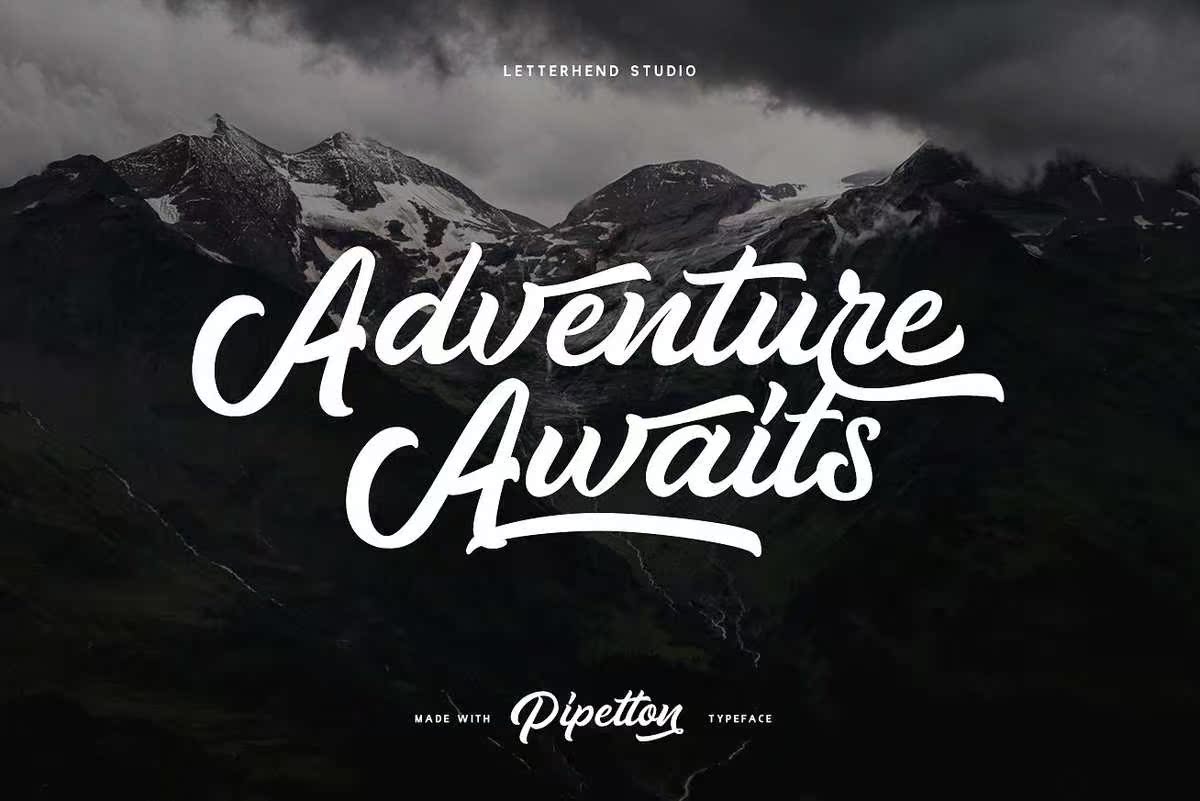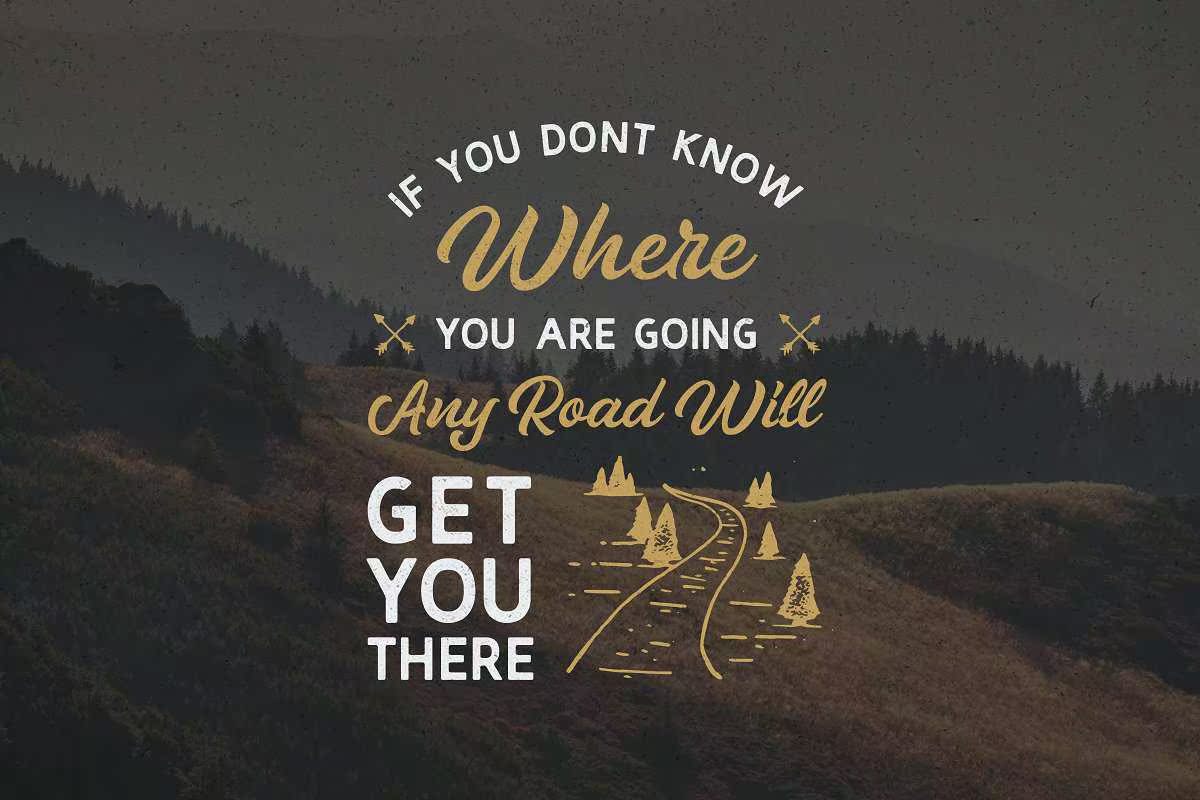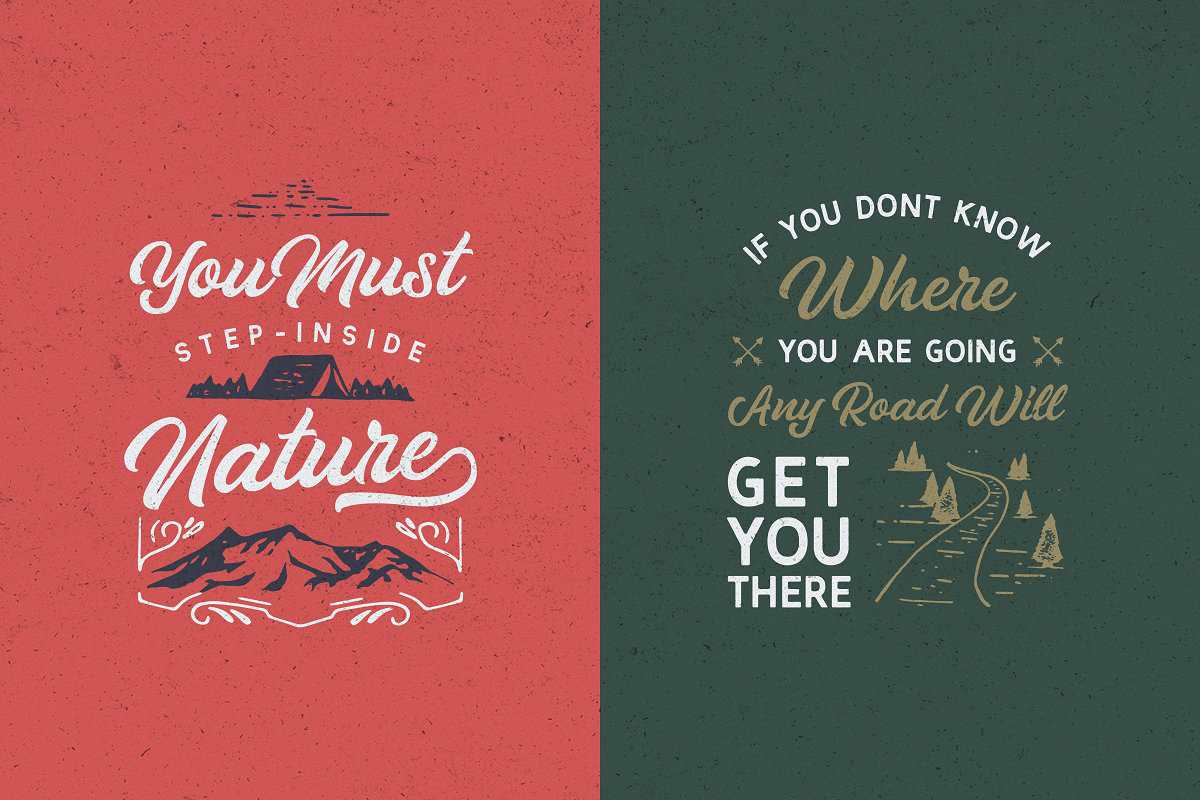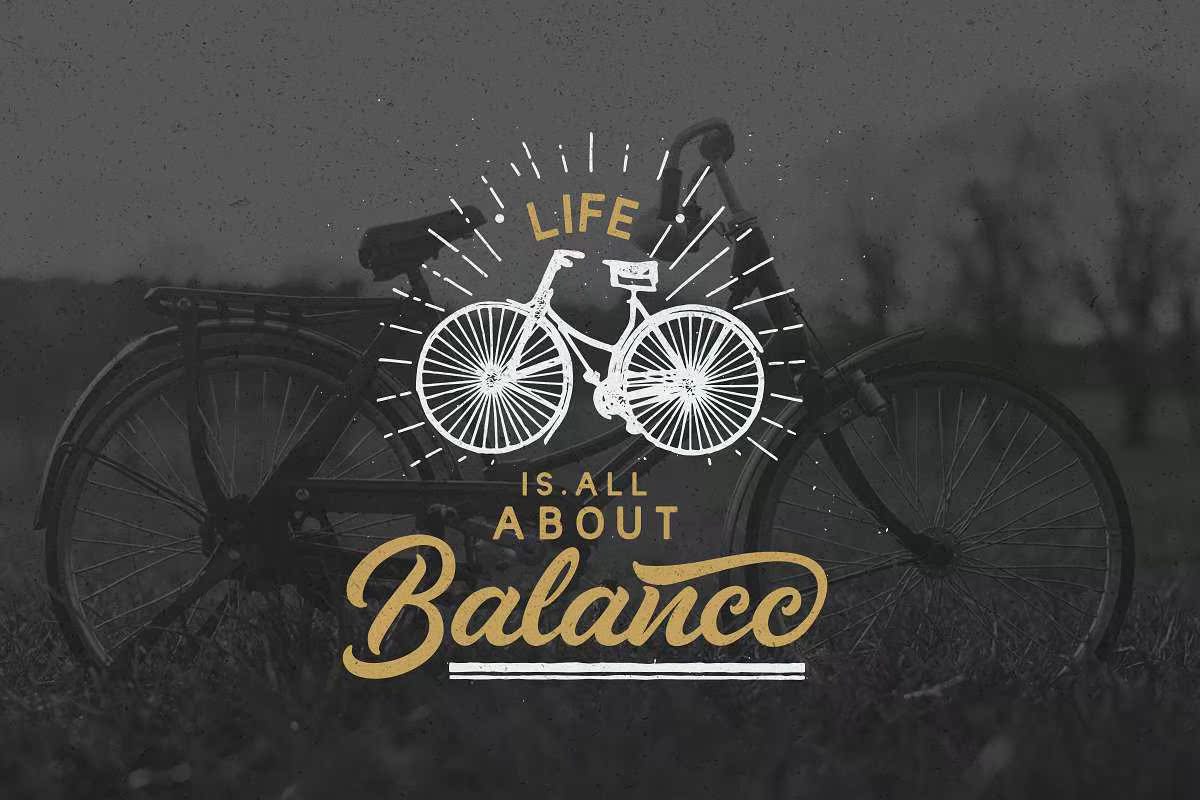
此字体由两种字体组成,分别是主脚本字体和互补字体,以及完全匹配的字体。此字体可使用易于识别的字体/文字标记/标签等,其字体和粗体字符使其不受排挤。此字体包括大写、小写、标点符号、符号和数字、样式集替换、连字和Swash。此字体由两种字体组成,主脚本字体和补遗是完全匹配的字体。此字体可使用简单的字体/文字标记/标签等,其字体为空白和粗体字符,并可从列表中删除。此字体包括大写、小写、标点符号、符号和数字、样式集替换、连字和斜杠。